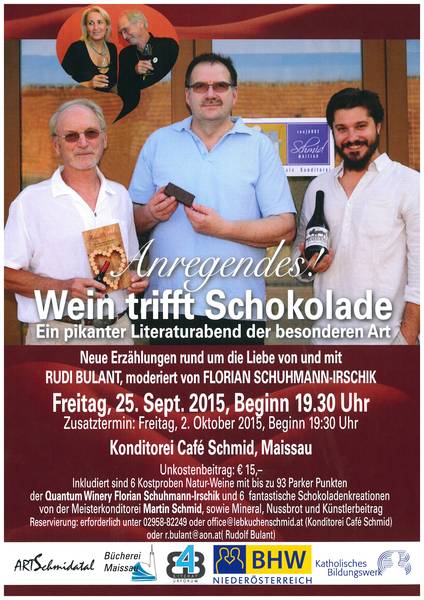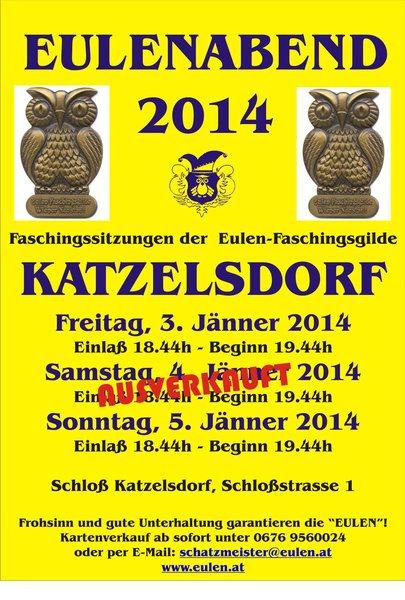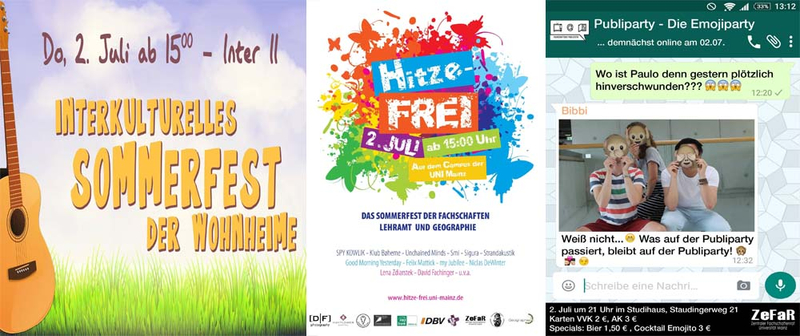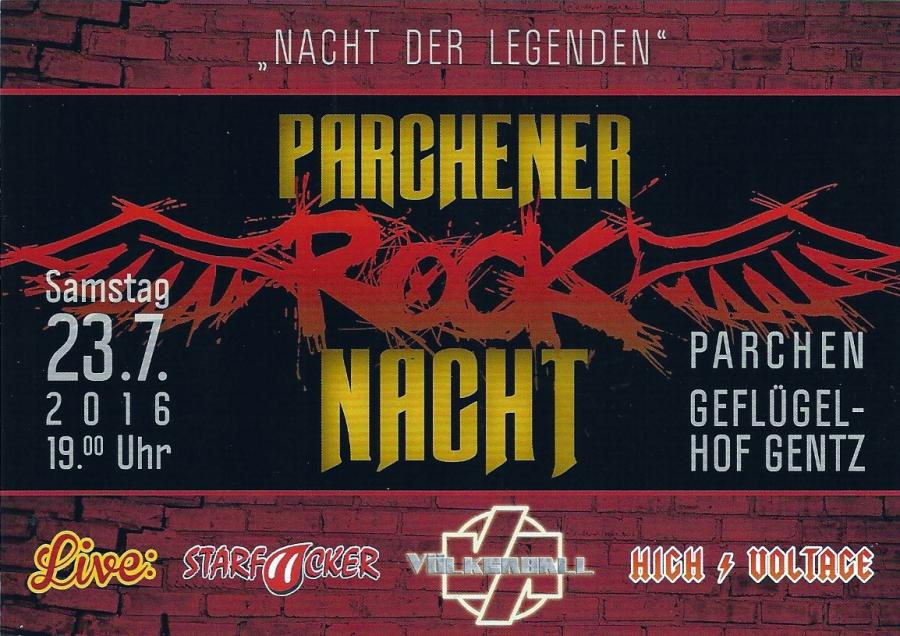
Und gleich eine Frage: Die Angabe von Minuten bei Uhrzeiten... darf man dieses Hochstellen (auf Plakaten) oder ist dies eher ein Fail?
Man darf. Aber wenn man Stunden und Minuten angibt, dann scheint es ja gerade auf die Minuten auch anzukommen. Von daher erscheint es mir widersinnig, gerade diese Angabe dann kleiner und damit schlechter lesbar zu machen.
kleiner und damit schlechter lesbar
Was bei Plakaten aber nicht notwendigerweise so sein muss. Da ist die Schrift oft ohnehin so groß, dass noch größer keinen Lesbarkeitsgewinn mehr bringt. (Und viele Plakate werden ja nie aus großer Entfernung betrachtet.) Andererseits könnte aber gerade die Abweichung von der Grundlinie und der Schriftgröße das Auge des Lesers auf die Uhrzeit ziehen.
Das hängt wohl, wie so oft, von der Umsetzung im Detail ab. :-?
Die Darstellung der Zeit zieht so ziemlich über die gesamte breite des A0-Plakat. Ich wollte das "Uhr" weglassen und wollte deshalb die Angaben der Minuten, auch wenn sie hier keinen Sinn ergeben, anführen.
So in der Art habe ich mir es gedacht.
Beginn: 18⁰⁰ | Einlass ab: 17⁰⁰
So ganz sicher bin ich mir aber noch nicht.
Hmm, ich denke: Uhr ja, h nein. Letzteres ist mindestens so unkonventionell wie 18⁰⁰, aber obendrein auch noch verwirrend (um nicht zu sagen komplett falsch). 2 h sind zwei Stunden, nicht zwei Uhr. Im Deutschen haben ich 18 h für 18 Uhr auch noch nie gesehen.
Da fällt mir ein, dass ich ja noch das Buch „Detailtypografie“ hier liegen hab. Demnach ist das Hochstellen von Minuten ok. Was bei „00“ passiert, steht nicht da ;-).
ich glaube, ich schaue mir es morgen noch einmal an um zu sehen wie es wirkt. Bis jetzt bin ich der Meinung, das „00“ besser aussieht als die Angabe Uhr.
Mag sein, aber dann ist das die Meinung einer kleinen Minderheit der Plakatgestalter. Ich habe mich jetzt mal durch (gefühlt) hunderte googlebare Veranstaltungsplakate geklickt und lediglich zwei mit deiner präferierten Schreibung gefunden. Missverständlich ist das m.E. nicht, sondern höchstens stilistisch ungewöhnlich.
Seltener ist nur die 18h-Variante, die ich auf einem deutschsprachigen Plakat (na ja, wenn man »deutschsprachig« entsprechend weit definiert :aschehaupt:) nur ein einziges Mal gefunden habe:
Ist diese Variante in Österreich vielleicht wirklich weiter verbreitet? :-?
Ansonsten benutzen fast alle Plakate anscheinend mehr oder weniger willkürlich 18 Uhr, 18.00 Uhr, 18:00 Uhr oder 18.00 [ohne »Uhr«], manchmal sogar verschiedene Varianten auf einem Plakat!
Und wenn ich darüber nachdenke, habe ich die 18.⁰⁰ oder 18⁰⁰ - Schreibweise wohl hauptsächlich an Ladentüren gesehen:
Mo-Fr 9⁰⁰-18³⁰
Sa         9⁰⁰-12⁰⁰
Ladentüren
Jetzt, wo du's erwähnst, fallen mir auch diese Schwarz-auf-Silber-Schildchen ein ...aber die sehen dann – auch wenn sie neu sind – irgendwie immer so nach 60er aus.
Letzteres ist mindestens so unkonventionell
Nach der Dudenseite wäre aber auch ein nicht hochgestelltes h als Uhrzeitangabe ok ...
Hochgestellte Ziffern kenne ich auch, mit zusätzlichem Punkt fällt mir das aber erst heute und hier auf ;-)
So, habe mir überlegt bei der 18⁰⁰-Schreibweise zu bleiben. Einfach aus Platzgründen.
Steht z.B. "Beginn" vor der Zeit, gehe ich mal davon aus, dass die Leute wissen, dass es um die Uhrzeit geht. Schreibt man 18 Uhr, würde es in meinen Fall zu "klobig" wirken. Man könnte "Uhr" quasi Hochstellen, das Ergebnis wäre dann aber gleich 18⁰⁰.
Bei meiner Suche habe ich auch oft die Schreibweise 18 h bzw. 18 H, würde ich aber nur nutzen, wenn wirklich wenig Platz ist oder sowieso wenig mit Text auf dem Plakat gearbeitet wird.
Meint ihr nicht auch, dass die Schreibweise in Nachrichten sich mit dem Übergang von Dumb- zu Smartphones komplett verändert hat?